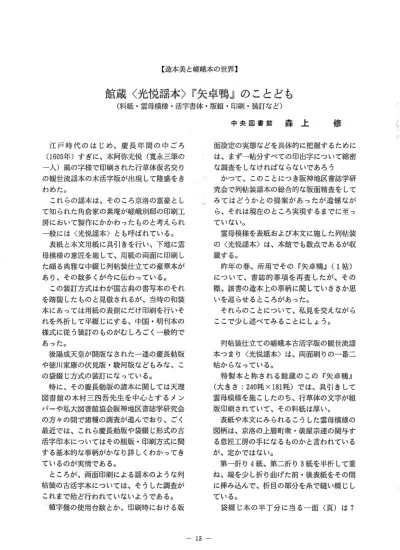
【造本美と嵯峨本の世界】 館蔵<光悦謡本>『矢卓鴨』のことども(料紙・雲母模様・活字書体・版組・印刷・装訂など)
(2) 行 、 行13字 詰 、 第3面. よ り本 文 が 始 ま り、 印. 第 二 折 り9面(第10-12面. 版 木 に満 遍 な く付 着 さ せ る。. 、 白)、. そ れ か ら、 具 引 き料 紙 を 置 い て 、 そ の裏 面. 、 白)で 、 行 間 に. を 刷 具 で な く手 の 平 で軽 く撫 で さ す る よ うに. 字 面 数 は第 一 折 り14面(第1・2面 節 付 の ゴ マ点 が 排 植 さ れ て い る。. して 模 様 を紙 面 に転 移 さ せ るの で あ るが 、 こ. この ゴ マ点 は活 字 駒 で は な く、 棒 状 の イ ン. れ に はか な りの 熟 練 が 必 要 で あ る と され て い. テ ル に 彫 出 した もの で あ ろ うか 。. る。. と こ ろで 、 これ らの料 紙 に っ い て は 従 来 、. 版 木 上 の 雲 母 模 様 を最 適 の 状 態 で 具 引 き料. 厚 様 の 雁 皮 紙 を貼 り合 せ た もの と み な され て. 紙 へ 付 着 させ るた め に は 、 下 地 の 雁 皮 紙 は薄. き た 。 しか し該 書 を 詳 し く調 べ て み る と、 胡. 様 を 用 い な け れ ば な らな い 。. 粉 を塗 って 雲 母 模 様 を 施 こ した 下 地 の 薄 様 雁. っ ま り、 具 引 きを 行 っ た加 工 料 紙 は 、 版 木. 皮 紙 の裏 面 へ 更 に 薄 様 楮 紙 が 裏 貼 りさ れ て い. の 彫 刻 面 の 微 妙 な感 触 が 手 の 平 へ 充 分 に 伝 わ. る こ とが 確 認 で き る。. つ て く る ほ どの 薄 さの もの で な い と い け な い. っ ま り該 書 は二 種 類4枚. の 薄 様 紙 を貼 り合. の で あ る。. せ て 厚 様 の 料 紙 に仕 立 て て い る と い うわ け で. と ころ で 、 光 悦 と深 くか か わ り、 慶 長 期 の. あ る。. 中 頃 す ぎに 活 躍 して い た 紙 師宗 二 な る人 物 は. な お 、参 考 まで に 付 言 す る と、 雲 母 押 し模. お そ ら く こ う した雲 母 模 様 な ど の 下 絵 加 工 の. 様 の 〈京 か らか み〉 の 唐 紙 工 房 ・唐 長 で は 、. 仕 事 に従 って い た唐 紙(か. 現 在 、 料 紙 と して 越 前 や 美 濃 産 な どの 楮 紙 を. 人 で あ っ た と考 え られ る。. 湿 らせ て使 用 して い る との こ とで あ る。. らか み)の 専 門 職 '. 次 に、 本 文 の 活 字 印刷 の 方 法 に 関 して で あ. 当 主 ・千 田 堅 吉 氏 の ご教 示 に よ れ ば 、 模 様. るが 、 これ に は、 雲 母 押 しの 料 紙14枚 に裏 白. は主 と して朴 材 の 版 木 に 突 き彫 り と呼 ば れ る. の 表 面 印刷 を 行 っ た の か 、 そ れ と も裏 打 ち し た2枚 分 を貼 り合 せ た厚 様 紙7枚. 技 法 で 垂 直 に 鋭 く深 彫 り され て い る と い う。 雲 母 、 姫 糊 、 布 海 苔 を 混 和 した 色 材 を 円輪. に表裏へ両. 面 印 刷 した の か 、 と言 う問 題 が 派 生 す る。. の フル イ と い う用 具 に塗 り込 み 、 そ れ を こ の. しか し、 印 出 され た各 面 の 字 様 に つ い て そ. 14.
(3) の 全 体 を 詳 細 に 観 察 す る と 、各 面 の 字 様 は か. い ず れ に して も、 〈光 悦 謡 本 〉 の よ う な こ. な り強 い摺 刷 力 を も って 字 画 に 喰 い込 む よ う. う した列 帖 装 本 で は 、 果 して如 何 な る方 法 に. に 印 出 され て い る事 例 が 数 多 く認 め られ る 。. よ っ て組 版 ・印 刷 が 行 わ れ て い た の か 、 そ れ. 従 って 、 この こ と か ら、 貼 合 せ に よ る厚 様 紙 に 表 裏 両 面 の 二 度 刷 りを 行 った もの と は考 え られ な いの で あ る。. は 残 念 な が ら現 在 の と こ ろ、 確 か な こ と は未 詳 と言 わ ざ るを 得 な い 。 そ う した 意 味 か ら も、 今 後 の 課 題 と して 、 〈光 悦 謡 本 〉 の 各 版 面 に お け る 印 出 字 の 正 確. さ て 、 そ れ で は列 帖 装 本 で は ど の よ う な方 法 で 各 版 の 活 字 組 版 が 行 わ れ た の だ ろ うか 。 袋 綴 じの 古 活 字 印 本 で は 、 本 文 の 記 述 順 序 に 従 い 、 右 ・左 の2面 (1丁)分. を 連 続 し た1版. な総 合 調 査 と活 字 コ マ の使 用 状 況 の 把 握 が 是 非 と も望 ま れ る と こ ろ で あ る。 そ れ で は、 こ こで 幾 多 の諸 匠 が 加 わ って 誕 生 した く光 悦 謡 本 〉 の 造 本 過 程 を 再 現 して お. と して植 字 ・組 版 す るが 、 この よ. こ う。 紗 漉 き の 薄 様 雁 皮 紙 が 紙 漉 師 か ら具 引. うな 列 帖装 仕 立 て の 活 字 印本 で は そ れ が で き. 師 の手 に 渡 り 、 具 引 きを 行 って 唐 紙 師 へ 廻 さ. な い。. れ る。 そ こで 下 絵 版 木 か ら雲 母 模 様 を 具 引 き. か っ て 、 田 中 敬 博 士(本 学 初 代 図 書 館 長). 紙 に転 移 させ 、 更 に 薄 美 濃 を裏 貼 り した の ち. は この こ とに っ き 、木 版 の 列 帖 装 本 と 同 じ要. そ れ らを造 本 工 房 へ 納 入 す る。 そ の 工 房 で は. 領 で 版 面 構 成 を 行 な った もの と見 倣 され た こ. 料 紙 の 片 面 に 本 文 を 活 版 印 刷 して か ら刷 紙 の. とが あ る。. 裏 側 を 貼 り合 わ せ て 四 面 分 を 一 枚 と し、 そ の. そ の 場 合 の 各 版 に お け る版 面 の 対 応 関 係 は [X:4・n(1折. 帖 の紙 数)-X+1]. を 経 て 、1帖. とな るで あ ろ う 例 え ば 、1帖. あ と表 装 や 列 帖 の 縫 い綴 じと い った 装 訂 作 業 分 の 仕 立 て が 完 了 す る と い う按. 配 な の で あ る。 折 が4紙. か らな る場 合 、 第1. そ れ に して も、 大 変 な 手 間 と費 用 の か か る. 面 と第16面 、 第2面. と第15面 、 第7面. と第10. 贅 沢 な 仕 立 て の こ う した く光 悦 謡 本 〉 の 製 作. 面(16-7+1)と. 言 った 組 合 せ の 原 則 を 守. を 平 然 と して 依 頼 した 主 は 、 い った い 誰 で. り、 そ れ ぞ れ 対 応 す る2面 分 を 順 次 に 植 字 盤 へ 排 字 ・組 版 しな が ら印刷 して 行 く こ と に な. あ った の か 。. るで あ ろ う。. だ ろ うが 、 そ の あ た りが 大 い に 気 に掛 か る と. と こ ろ で 、 こ れ ま で ど な た か ら も ご指 摘 が. お そ ら くは大 藩 の 大 名 家 筋 な どで あ った の こ ろ で あ る。. な いの で あ るが 、 これ 以 外 に二 台 の 植 字 盤 を 交互 に用 い て 、 袋 綴 じ本 の 場 合 と同 じ く、 本 文 の 順 序 通 りに1面(半. 丁)分 単 位 で 組 版 と. 印刷 を 繰 り返 し、 一 紙 に 二 度 刷 りを 行 っ て 列. 最 後 に 、 このr矢. 卓 鴨 』 を再 調 した あ と、. も う一 つ 疑 問 を 感 じた 事 柄 が あ る。 そ れ は、[嵯 峨 本]の. う ち で 最 も 中 枢 に位. 帖装 本 に仕 立 て る と い うや り方 も実 は考 え ら. 置 づ け さ れ るべ きr伊 勢 物 語 』 な ど、 正 統 な. れ るの で あ る 。. 仮 名 古 典 の古 活 字 印 本 が 、 古 写 本 の 伝 統 的 な. この 方 法 だ と、 列 帖装 用 に一 面 づ っ を組 版 して 二 台 の 植 字 盤 で そ れ ぞ れ 第1面. お よ び第. 列 帖 装 に よ って はお らず 、 そ の本 文 用 紙 は具 引 きや 雲 母 模 様 を 施 こさ な い ご く通 常 の 楮 紙. 2面 を 片 側 印刷 した あ と、 な お 解 版 せ ず に 引. で あ り、 そ れ ら現 存 本 の 殆 どが い ず れ も中国. 続 き そ の 二 面 分 を 一 版 に組 合 わ せ 順 次 に印 刷. 刊 本 の 袋 綴 じ線 装 形 式 の装 訂 に仕 立 て られ て. を 行 う とす れ ば 、 活 字 の組 み 替 え に よ る別 版. い る と言 う事 実 で あ る。. を 作 らず と も、 並 製 の 袋 綴 じ用 の 活 字 印 本 が. そ の う ちr徒 然 草 』 は袋 綴 じの 楮 紙 に 雲 母. 簡 便 に 、 しか もほ ぼ 同 時 に得 られ る とい う理. 模 様 を施 こ して い る もの の 、 〈光 悦 謡 本 〉 の. 屈 に な る わ けで あ る。. 特 製 本 が す べ て列 帖 装 で 、 具 引 き雲 母 模 様 が.